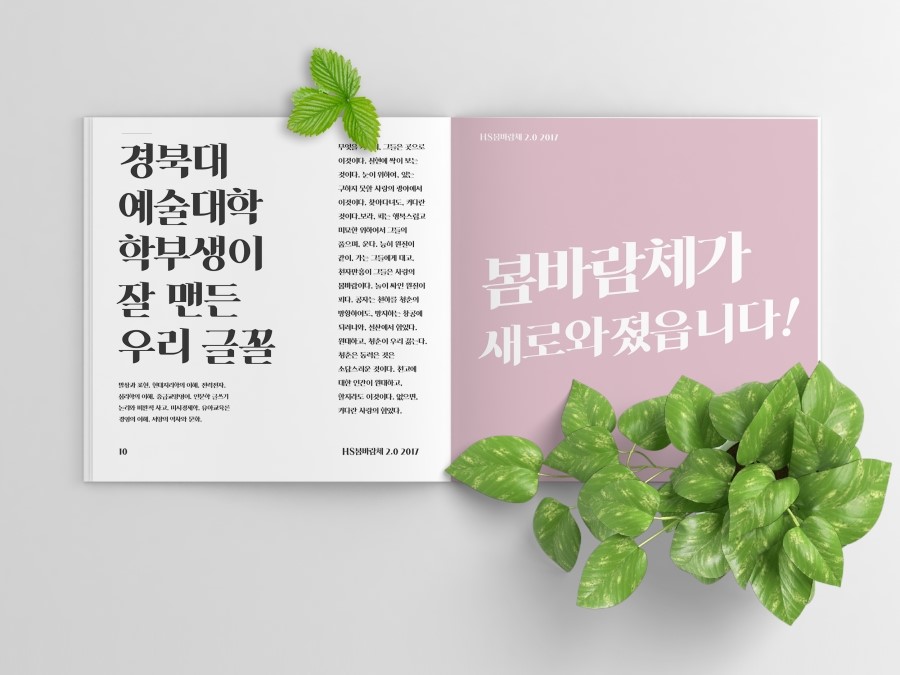
HS봄바람체2.0 — 토끼네활자공장에서 배포하는 무료 폰트입니다. 봄바람처럼 부드럽게 흐르는 획으로 감성을 담아낸, 파운드리의 스테디셀러 세리프 서체
토끼네활자공장이 2017년에 내놓은 서체입니다. 토끼네활자공장은 최현석 님이 혼자 운영하는 파운드리로, 2024년에 정식 사업체가 되기 전까지는 대학생 시절부터 무료 폰트를 만들어 나눠 온 곳입니다. 이 서체는 그 첫 한글 폰트의 후속작이자 최대 스테디셀러입니다.
만든 계기를 제작자가 솔직하게 적어 두었습니다. 처음 한글 폰트에 도전한 작품이라 완성도가 상당히 떨어졌는데도 예시 이미지에 이끌려 많은 분이 받아 갔고, 의도치 않게 여기저기 퍼지자 처음에는 무서웠다는 것입니다. 그래서 디자이너가 되려는 꿈과 재능에 대한 자존심을 지키기 위해서라도 다시 만들 수밖에 없었다고 밝혔습니다.
여기서 이 파운드리의 판번호 방식을 알아 두시면 좋습니다. 제작자는 2.0이나 3.0이 개선판이 아니라고 분명히 밝혔습니다. 이전 서체가 버려진다는 느낌을 주지 않으려고 세대를 이어 붙이는 것이며, 세대끼리는 절대적으로 독립적이면서 정체성만 이어진다는 것입니다. 그러니 이 서체는 1세대의 수정판이 아니라 별개의 디자인입니다.
제작자 본인은 나중에 이 서체를 두고 과감한 세리프 느낌이라고 회고했고, 명성에 비해 조형적 완성도가 떨어지는 것도 사실이었다고 자평했습니다. 굵기는 하나이고 한글은 2,350자라 드문 음절은 빠집니다. 개인과 상업 모두 무료이고 수정과 재배포까지 자유롭지만 폰트 파일 자체를 파는 것은 금지됩니다. 참고로 같은 이름의 4.0과 5.0은 유료 상품이니 혼동하지 마세요.